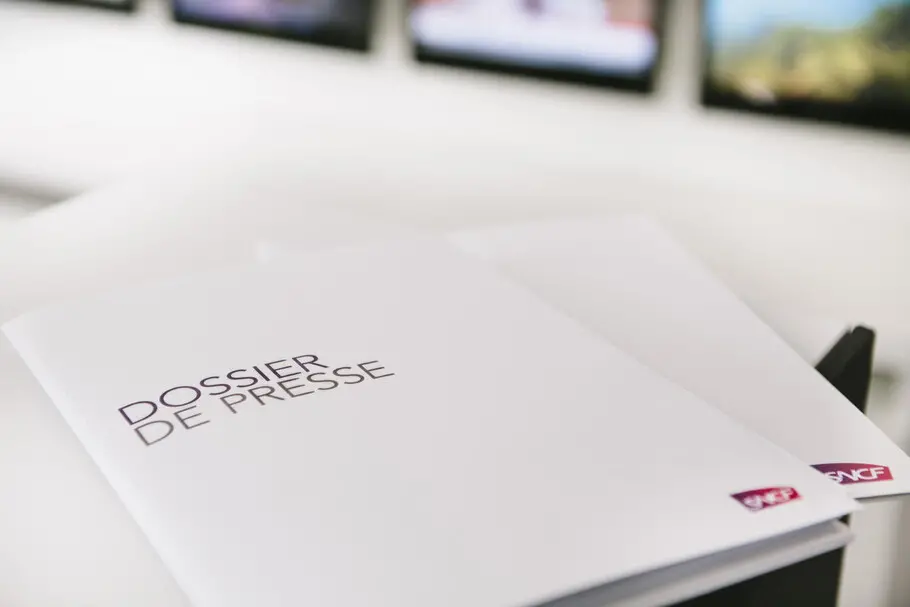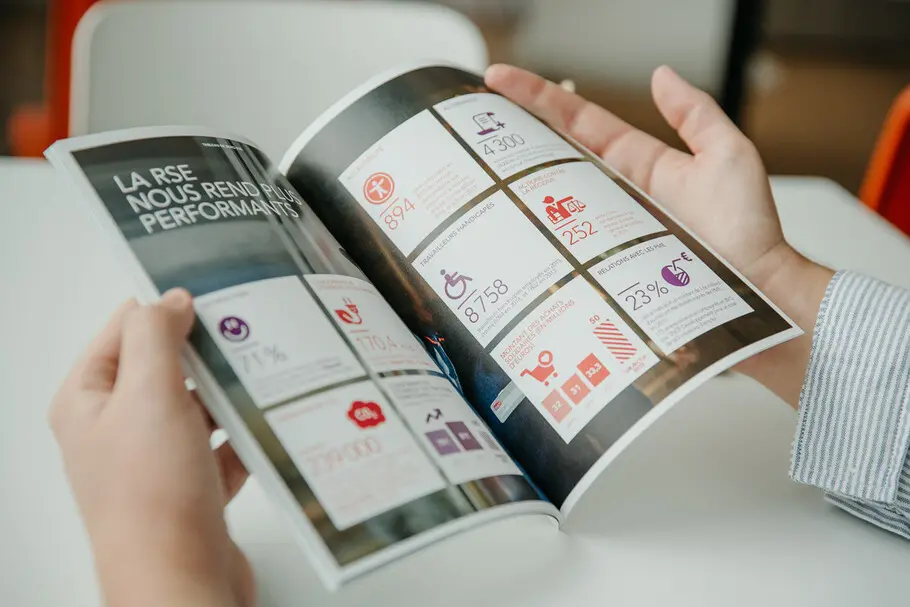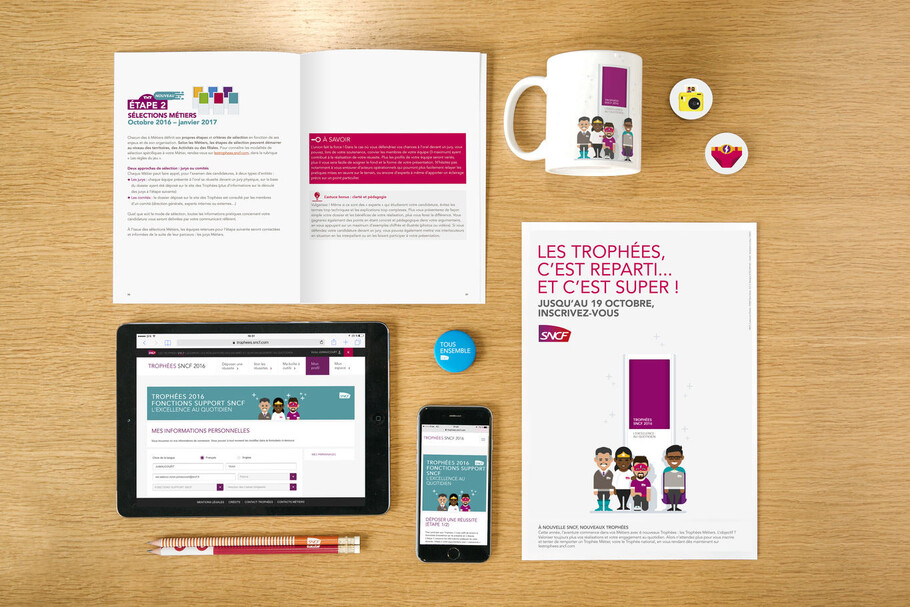
Design industriel et de marque : les deux atouts de la SNCF pour offrir des expériences client fiables et cohérentes.
“ La marque, en pleine évolution et se déclinant désormais en marques filles, avait besoin d’une police d’entreprise pour compléter son logo. ”
SNCF branding and design supporting a consistent customer experience.
La typographie d’entreprise, gage du succès intemporel actuel et futur de la compagnie nationale ferroviaire française.
La SNCF (Société Nationale des Chemins de Fer Français) est l’entreprise publique ferroviaire française. Fondée en 1938 et sise à Saint-Denis, en région parisienne, elle gère et exploite le réseau ferroviaire, y compris le réseau à grande vitesse TGV, en France et à Monaco. La SNCF dispose de deux sous-opérateurs, SNCF Réseau, qui gère le réseau ferré national, et SNCF Mobilités, chargé de l’exploitation des trains. Elle compte également environ 900 filiales. L’entreprise emploie au total plus de 260 000 personnes dans plus de 120 pays et exploite chaque jour 15 000 trains de marchandises et de voyageurs, transportant plus de cinq millions de passagers.
Le défi.
Si la concurrence est moins redoutable dans le secteur du rail qu’ailleurs, le succès d’une marque reste grandement lié à l’expérience client que celle-ci est capable d’offrir. Depuis ses débuts, la SNCF reconnaît l’importance que peut avoir le design lors de toutes les étapes de l’expérience client. En témoigne sa considération pour le design industriel, avec la création par Paul Arzens des locomotives “ nez cassés ” qui ont battu de nombreux records de vitesse et furent les figures emblématiques des chemins de fer français des années 1940 aux années 1970. Citons également le design du TGV par Roger Tallon, qui accorda une attention toute particulière à l’esthétique et à l’atmosphère dans les wagons. Des sièges aux couleurs, en passant par l’éclairage et jusqu’à la cartographie du réseau ferroviaire affichée dans chaque train : le designer industriel ne laissait rien au hasard.
À travers les âges, l’entreprise a remis plusieurs fois sa marque au goût du jour afin de l’aligner avec les intérêts modernes de sa clientèle. Le logo de la SNCF a, par exemple, été revu plusieurs fois en 80 ans :
• 1938 : monogramme circulaire dessiné par Maximilien Vox
• 1947 : écusson avec une carte simplifiée de la France et les initiales en diagonale
• 1967 : logo plus moderne avec lettres en gras et italique sur fond vert, symbolisant la robustesse et la vitesse
• 1986 : version simplifiée de la marque verbale par Roger Tallon, sans cadre et avec des lettres non pleines rappelant les rails
• 2005 : logo carmin et vermillon dessiné par Carré Noir
• 2011 : logo de 2005 légèrement redessiné
La marque, en pleine évolution et se déclinant désormais en marques filles, avait besoin d’une police d’entreprise pour compléter son logo. C’est pourquoi nous avons testé plusieurs polices de caractères avec des particularités de conception intrinsèques différentes, dans des contextes variés : bien éclairé ou faiblement éclairé et avec des couleurs différentes (texte noir sur blanc ou blanc sur noir).
La solution.
Qu’est-ce qui rend une police de caractères lisible ?
L’équipe de la SNCF est convaincue qu’une typographie forte est essentielle à la bonne perception de la marque. En collaboration avec Monotype, la SNCF a donc choisi la police Avenir. Ce choix a été motivé par le besoin d’efficacité dû à sa vaste utilisation, ainsi que par le désir de transmettre un message de fiabilité, de continuité et de robustesse à sa clientèle.
Par ailleurs, la police Avenir représentait la cohésion des éléments d’un style cohérent pouvant être repris par les marques filles de l’entreprise, même quand celles-ci gardaient leurs identités propres. La police devait également être intemporelle et suffisamment orientée vers l’avenir pour être présente dans les points de contact clients, y compris dans les trains SNCF, conçus pour circuler durant une trentaine d’années. Il s’agit d’une approche unique que les autres entreprises verticales n’ont en général pas à aborder. Pour assurer son succès, la SNCF devait garantir un accès à la famille de polices Avenir à toutes ses équipes de design ; Monotype a donc aidé la marque à déployer cette ressource sur plus de 22 000 postes de travail.
Le site du design d’entreprise le résume très bien : “[Avenir] est une police simple, ronde et facile à lire.”
À propos d’Avenir.
Conçue par Adrian Frutiger, Avenir a fait sa première apparition en 1988. Il s’agit d’une police de caractères géométrique sans Serif qui ne repose pas sur des lignes droites et des effets circulaires, mais conserve au contraire un style humaniste. Adrian Frutiger a dessiné Avenir non sans une dimension psychologique, apportant notamment de légères variations aux pleins et aux déliés dans le but de réaliser une harmonie de caractères qui n’aurait pas été possible avec des lignes purement géométriques.
“ Nous avons choisi Avenir parce qu’il s’agit d’une police simple véhiculant un message de fiabilité et de robustesse, deux critères essentiels pour nous. Nous exploitons 15 000 trains par jour. Nous n’avons donc pas droit à l’erreur et pour nous, Avenir incarnait bien notre organisation et ses atouts. ”
– Isabelle Patard, Responsable identité de marque et design
La lisibilité est restée essentielle, en particulier pour les points les plus petits. L’ajout de pointes émoussées (par exemple sur le A et le M) et les légères variations d’épaisseur de lignes0 des panses atténuent le côté strict de la police. Comme son nom l’indique, Avenir est bien plus qu’une police contemporaine ; c’est un clin d’œil à Futura®, conçue par Paul Renner, ainsi qu’à ITC Avant Garde Gothic®, par Herb Lubalin.
Résultats.
Grâce à son partenariat avec Monotype, la SNCF parvient à conserver une identité forte dans son évolution pour répondre aux besoins du marché, laquelle se traduit notamment par le lancement de marques filles comme Ouigo, une offre de voyages à bas coûts, et TGV inOUi, une offre de services premium. Les atouts d’Avenir pour la SNCF :
• Elle permet à nos créatifs en interne d’accéder aux polices de la marque nécessaires à la création d’expériences en ligne et hors ligne.
• Elle garantit l’homogénéité entre les canaux et les dif férentes marques filles.
• Elle assure l’avenir de la marque en la préparant à la fois aux besoins d’aujourd’hui et aux aspirations de demain.